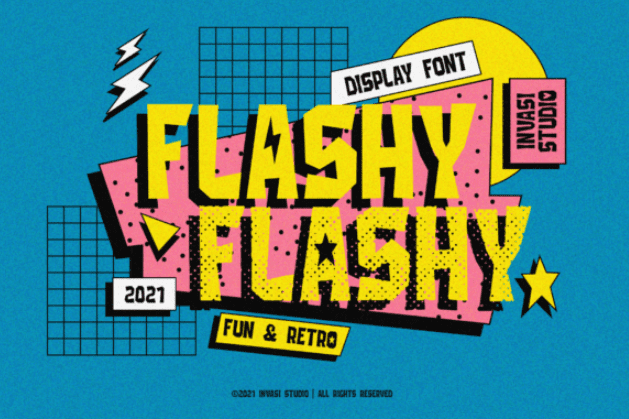
Название: Flashy Font (2021)
Flashy - это веселый ретро-шрифт.
Его современные и причудливые символы можно подобрать к большому количеству проектов, поэтому добавьте его в свои творческие идеи и обратите внимание, как он их выделяет!
Название: Flashy Font (2021)
Flashy - это веселый ретро-шрифт.
Его современные и причудливые символы можно подобрать к большому количеству проектов, поэтому добавьте его в свои творческие идеи и обратите внимание, как он их выделяет!